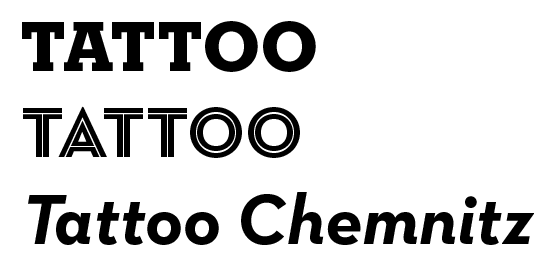
Schriftart für Tattoo-Studio ?
Nachtrag:
Mal unabhängig davon, ob der Apostroph an dieser Stelle richtig eingesetzt wird oder nicht oder ob er an dieser Stelle eingeführt werden sollte:
Bei »Elisabeths Fundstückchen« geht es um Elisabeth und um die Fundstückchen, nicht um den Buchstaben »s«, ob mit oder ohne Apostroph.
Wenn ich an solcher Stelle ein Apostroph sehe, werde ich von dem, was ich eigentlich auf Anhieb erfassen sollte, abgelenkt. Mir springt ein »’s« ins Auge. Noch schlimmer, wenn wie bei 90 % aller Fälle auch noch statt Apostroph ein Akzent benutzt wird, unter dem man Bälle durchwerfen kann.
Da will ich mich gar nicht dran gewöhnen, ich finde es unschön und letztendlich unleserlicher. :peng:
Ich stimme Dir zu. Und ich finde, dass ein zur Funktion als Auslassungszeichen hinzukommender zusätzlicher Einsatz des Apostrophs zur Kennzeichnung des Genitiv-s eher eine verwirrende als eine verdeutlichende Wirkung hätte, da dann zwei völlig unterschiedliche Sachverhalte auf gleiche Weise gekennzeichnet würden. Im Falle der ganz wenigen Namensbeispiele (Andrea/Andreas), bei denen die Anwendung des Genitivs Verwirrung über das Geschlecht aufkommen ließe, darf die Endung ja laut Duden bereits entsprechend gekennzeichnet werden. Mir persönlich genügt das dann aber auch. :)
Daniel Gauthier: Tattoo Parlour (Dingbats)
Aber die Koralle in Condensed scheint da etwas besser zu laufen?
Koralle? Gibt es die für den Rechner? Die kenne ich nur in Blei.